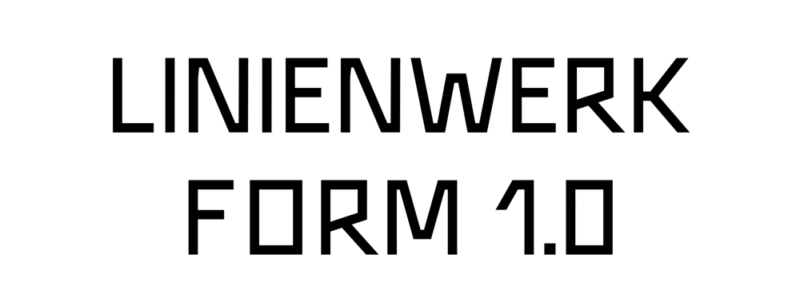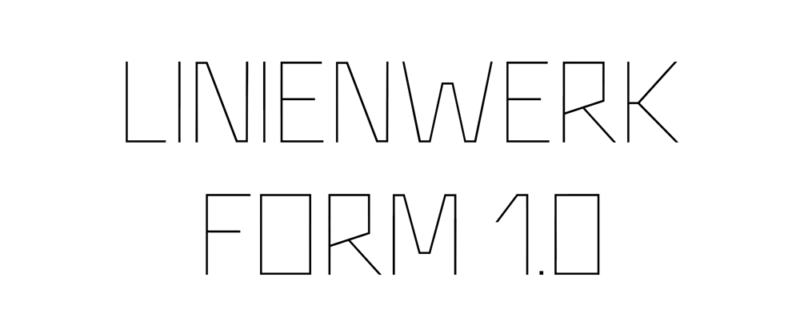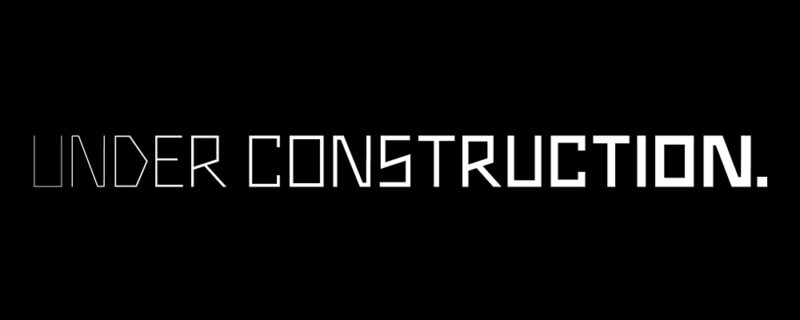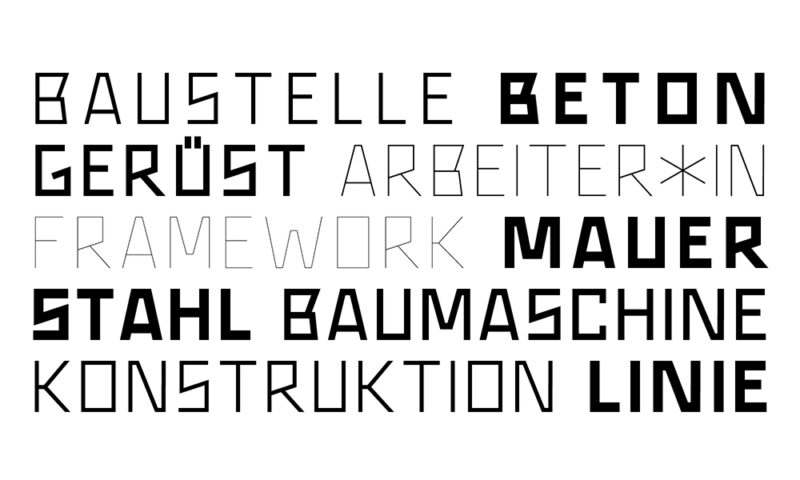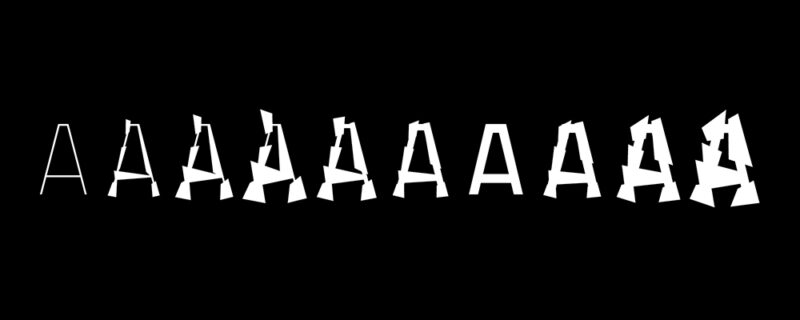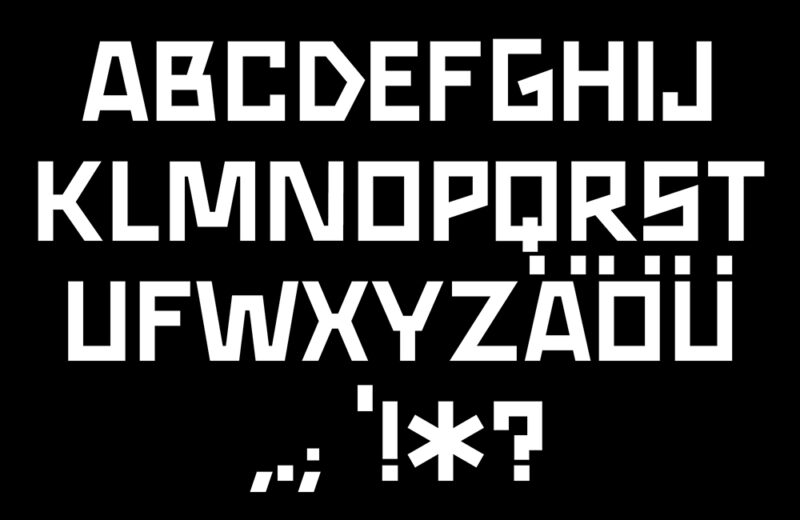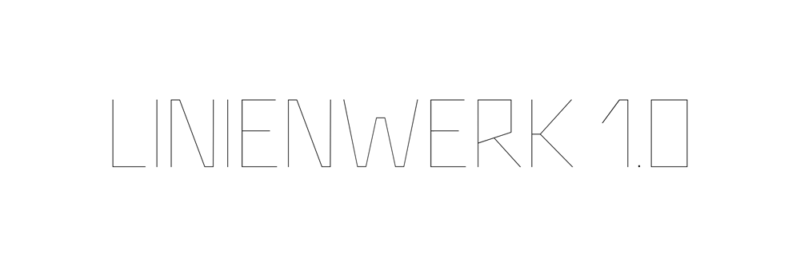
LINIENWERK
LINIENWERK ist eine variable Display-Schrift, bestehend aus Versalien. Als Monoline Schrift kombiniert sie konstruierte Linien mit harten Kanten und Ecken. Neben der klassischen Schrift LINIENWERK, welche sich von Ultra Thin bis zu Black stufenlos skalieren lässt, gibt es die Variante LINIENWERK FORM, welche die Linien mit Formen ergänzt und so ein neues Schriftbild generiert.